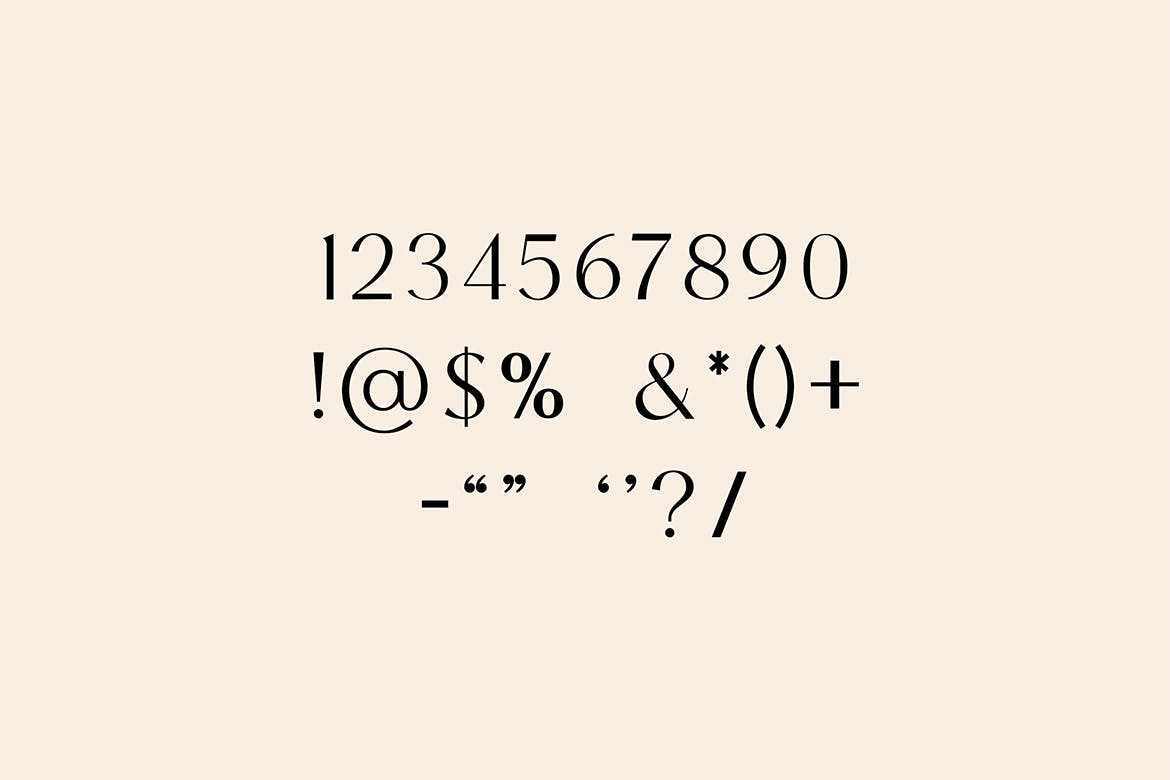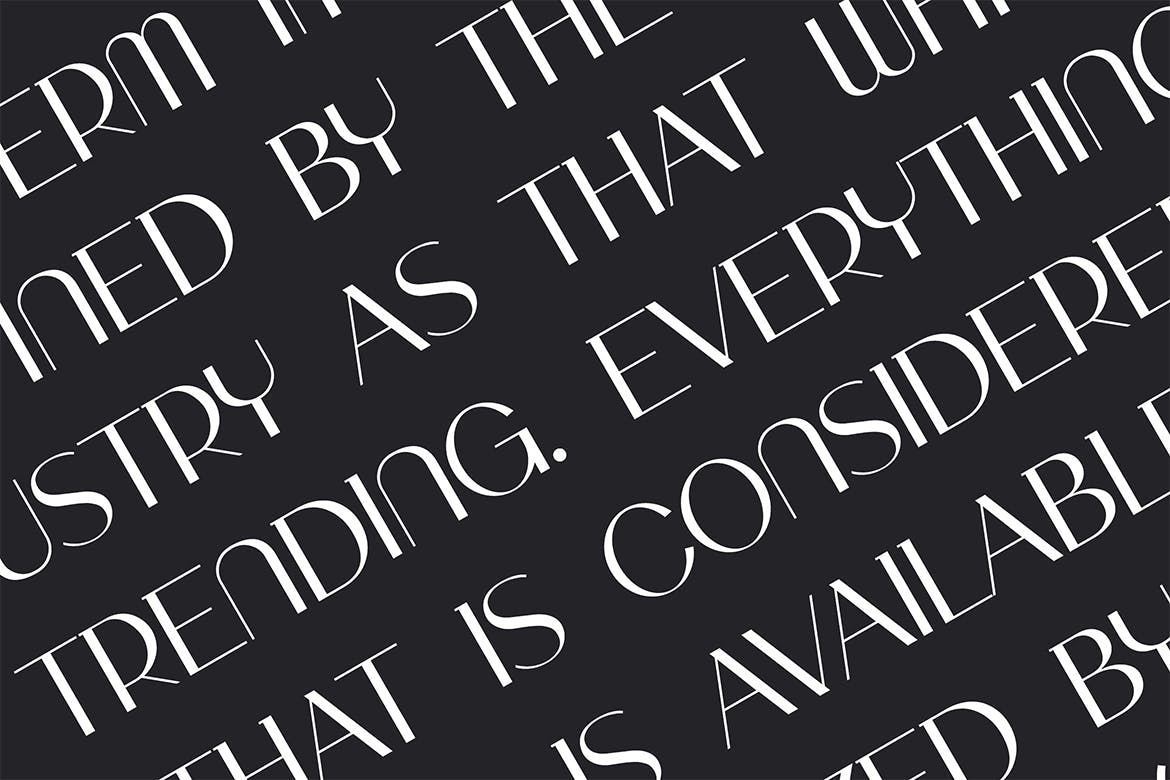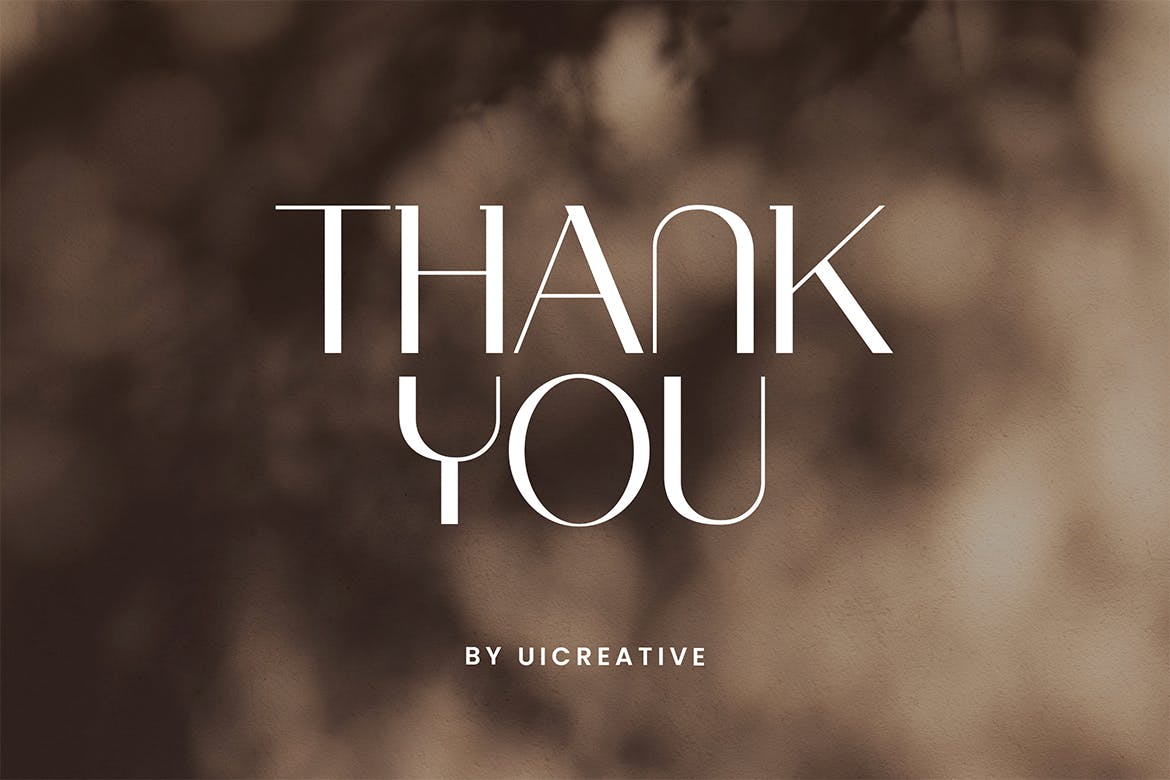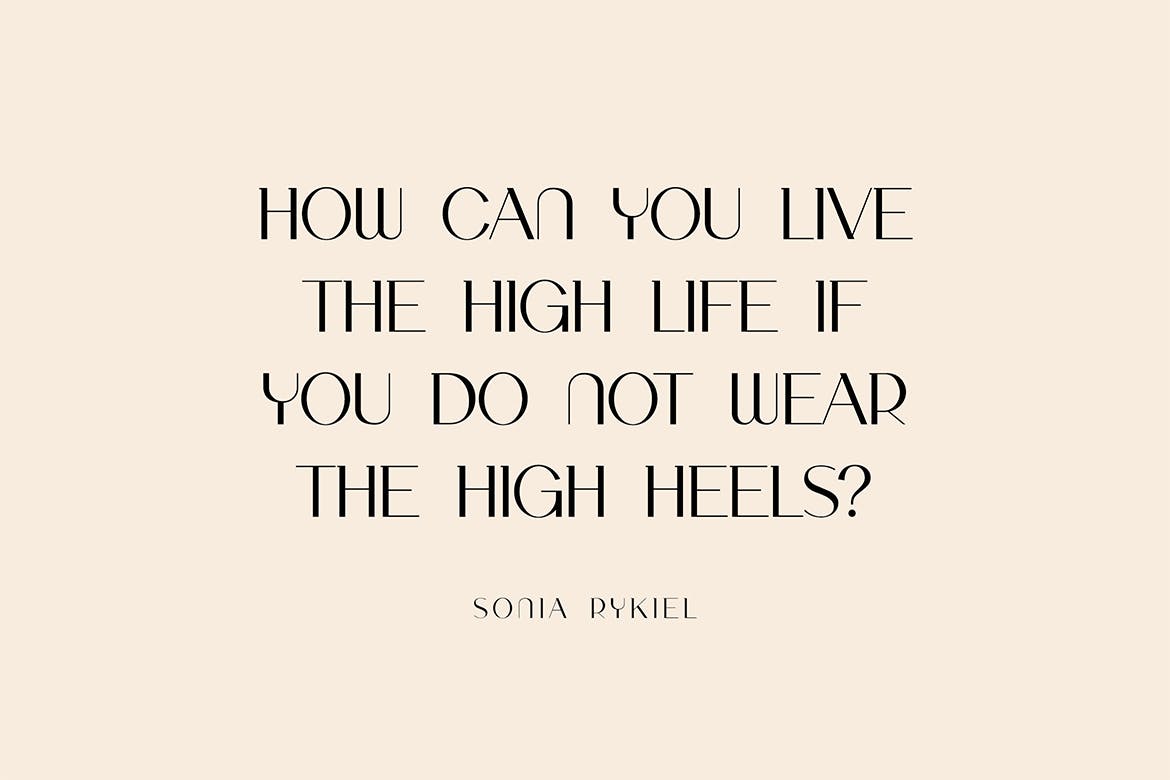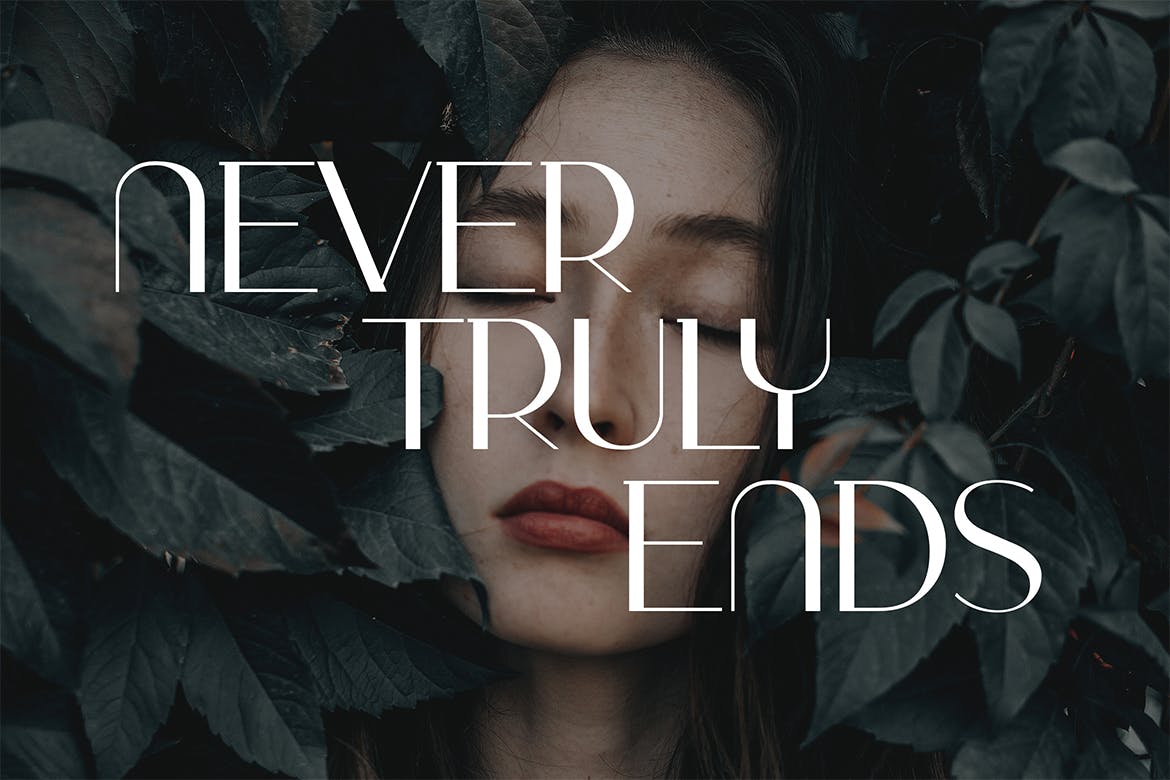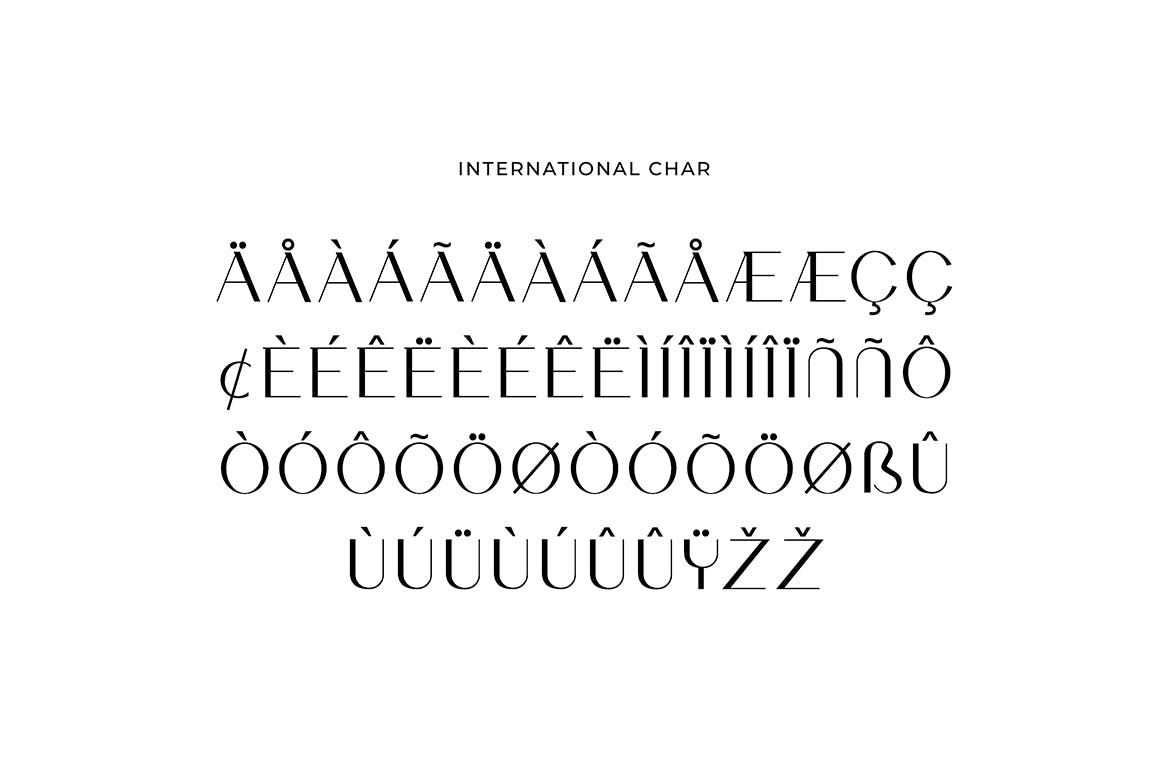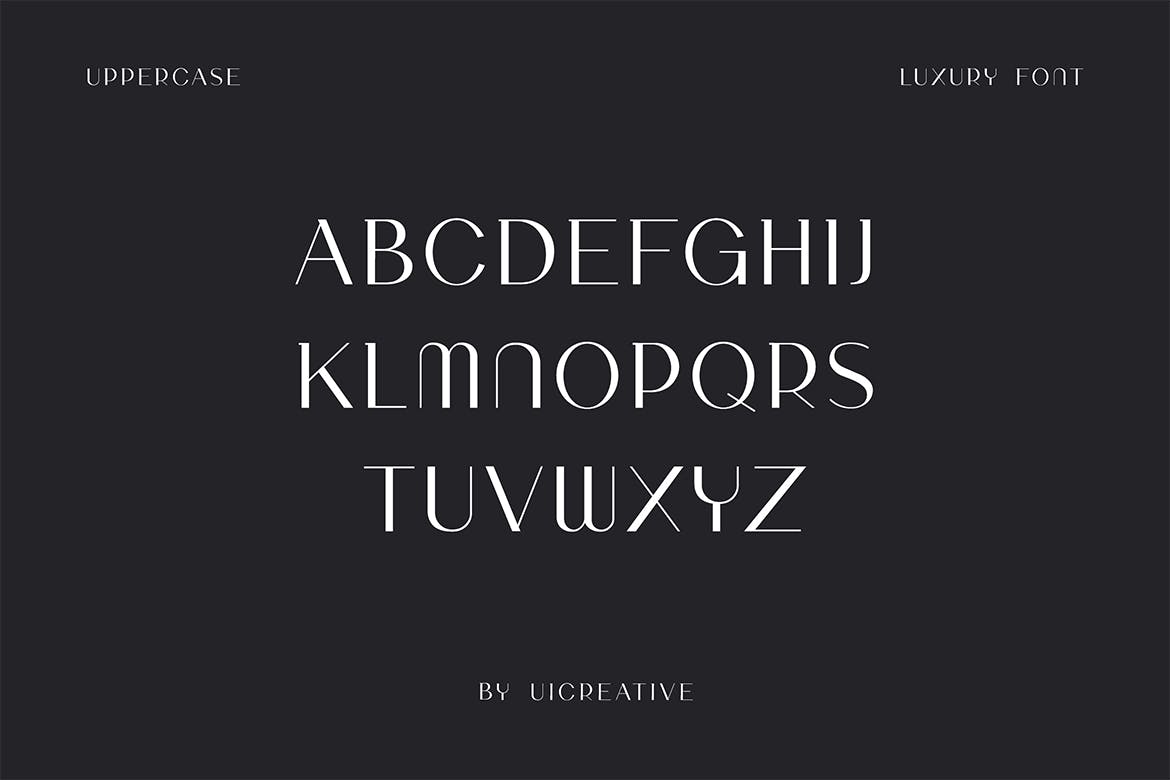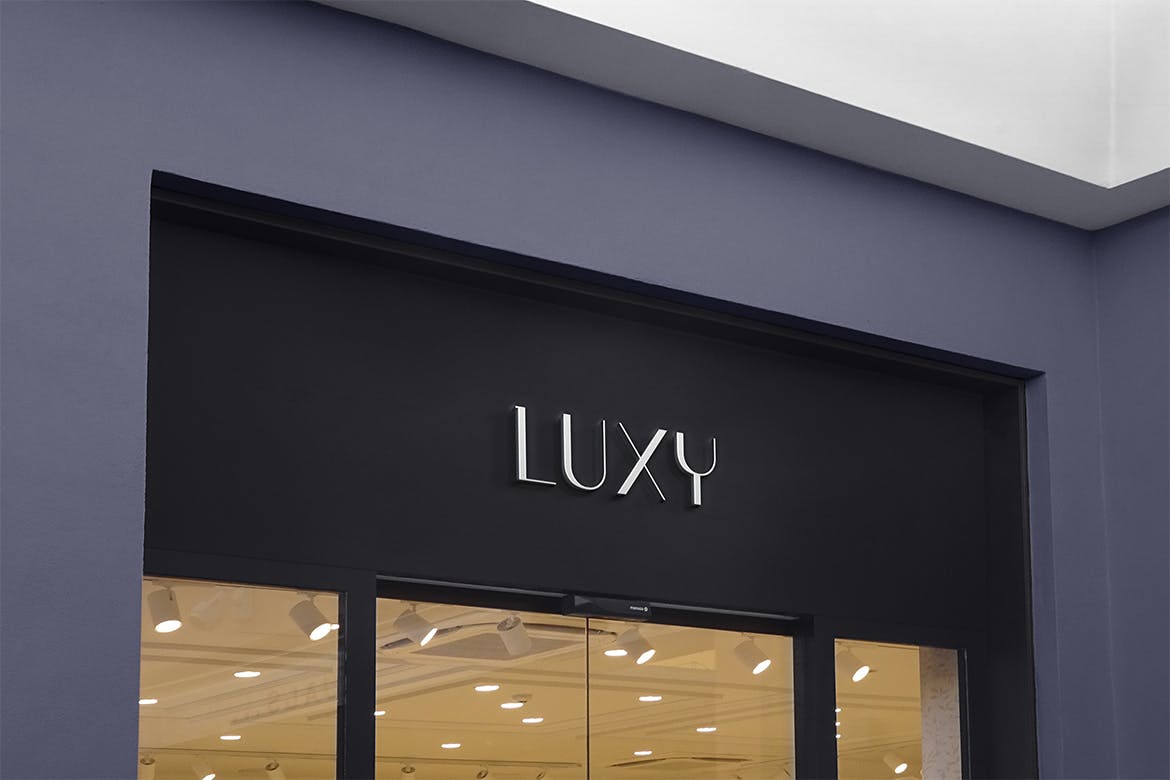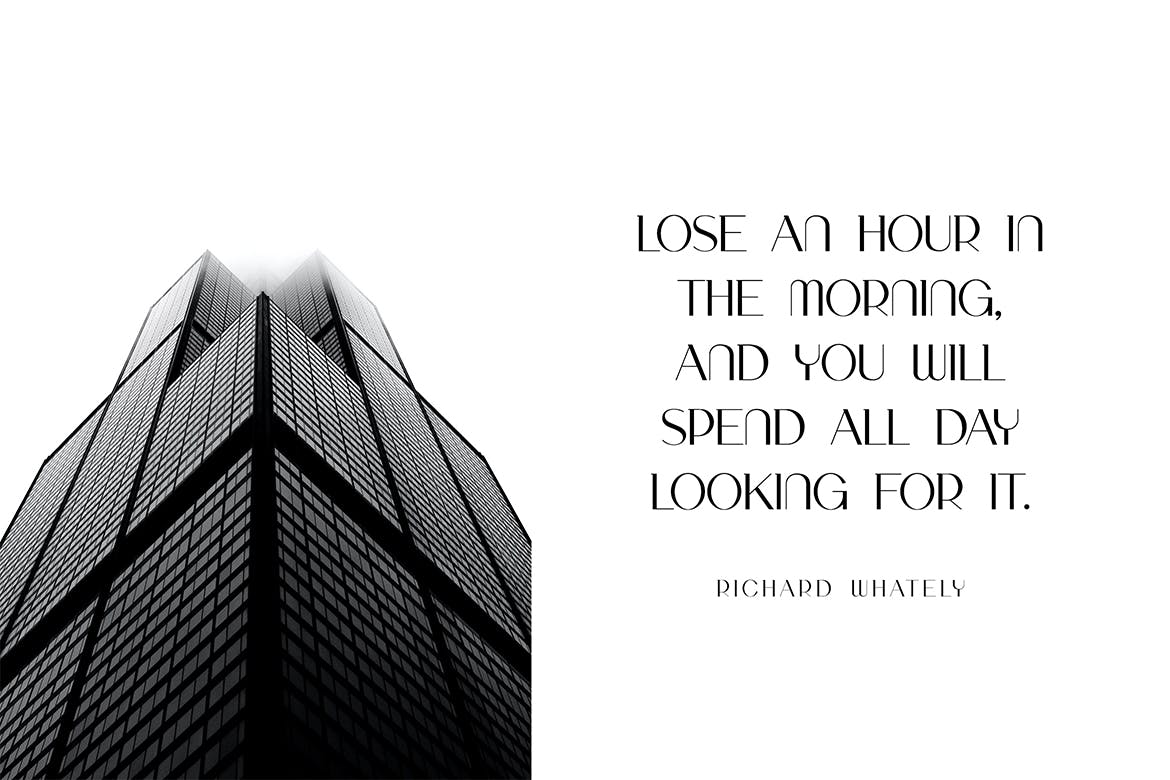
Ezme Luxury Sans Serif Font
فونت Ezme Luxury Sans Serif با طراحی زیبا و مدرن، مناسب برای پروژه‌های مختلف شما.
معرفی محصول جدید ما، فونت Ezme Luxury Sans Serif که با طراحی مدرن خود احساس زیبایی، کلاس و شیک بودن را به ارمغان می‌آورد. این فونت به‌طور کامل برای پروژه‌های متنوعی مانند امضا، لوازم‌التحریر، لوگو، عروسی، نقل‌قول‌های تایپوگرافی، جلد مجلات یا کتاب‌ها، سرصفحه‌های وب‌سایت، لباس، برندینگ، طراحی بسته‌بندی و بیشتر مناسب است. همچنین، طراحی برندینگ یا ویرایش مرتبط با مد، هر دو جنبه مردانه و زنانه را به نمایش می‌گذارد.
کاراکترهای پشتیبانی شده:
• ABCDEFoHIJÁLMNOPQRSTUVWXYZ
• abcdefghijklmnopqrstuvwxyz
• 0123456789
• !"#$&'()*+,-./:=?@[]_{|} ¡¢«»¿
• ÀÁÂÃÄÅÇÈÉÊËÌÍÎÏÑÒÓÔÕÖØÙÚÛÜÝ
• àáâãäåçèéêëìíîïñòóôõöøùúûüÿ
• ĀāĂ㥹ĆćĈĊċČčĎďĒēĔĕĖėĘęĚěĜĞğĠġĤĨĩĪī
• ĬĭİıĴĹĽľŁłŃńŇňŌōŎŏŔŘřŚśŜŞşŠšŤ
• ťŨũŪūŬŭŮůŴŶŸŹźŻżŽžǫ
• ȦɢɪɴʀʏʙʜʟᴀᴄᴅᴇᴊᴋᴍᴏᴘᴛᴜᴠᴡᴢẀẂẄẼỲ